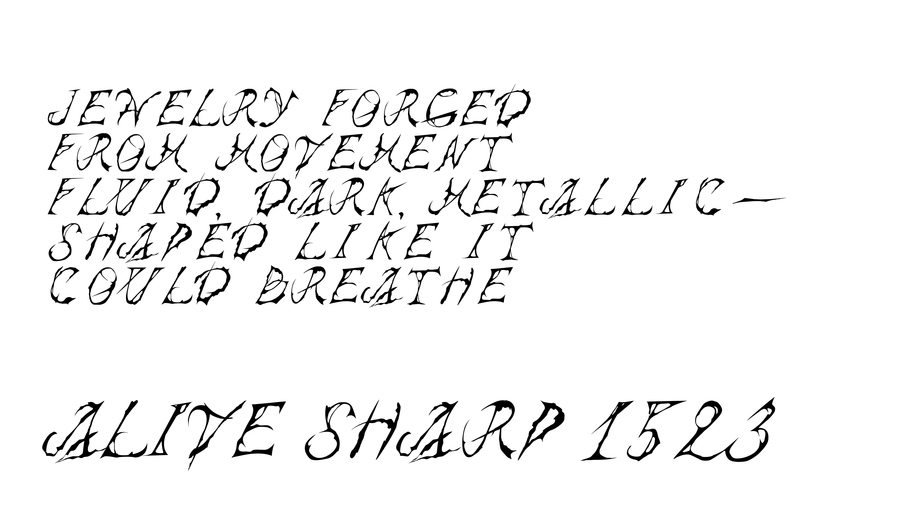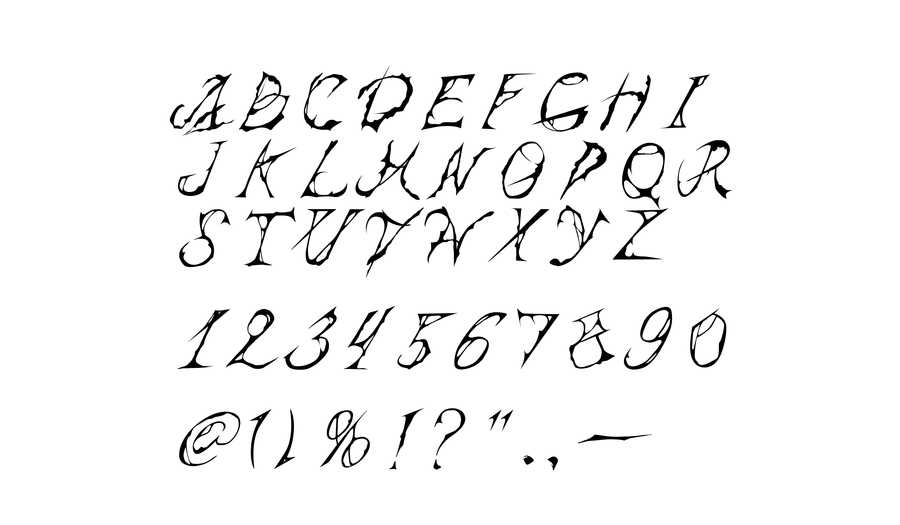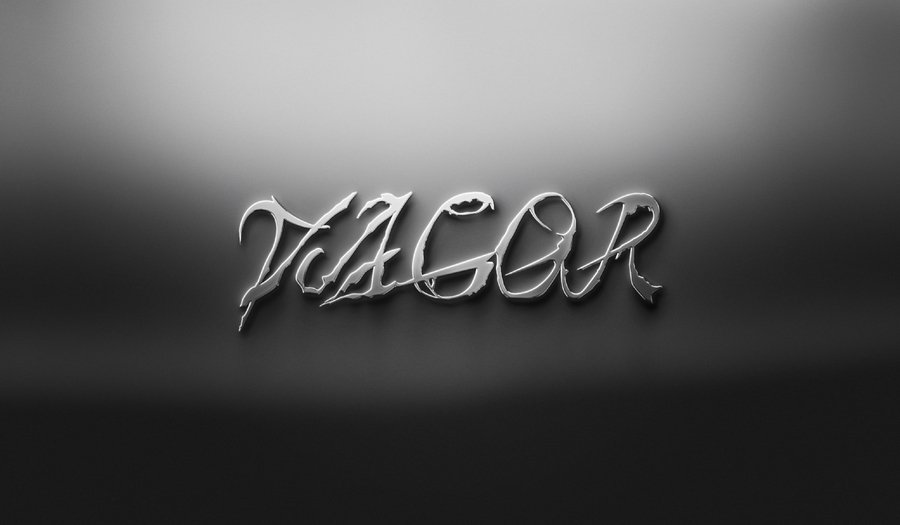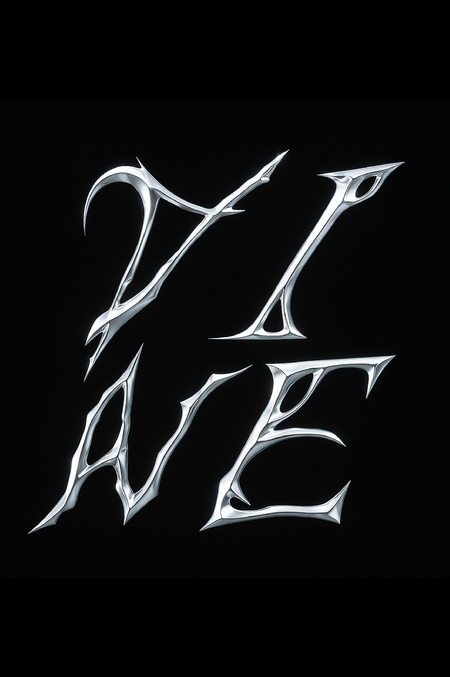
vine — акцидентный шрифт
Vine — это живой, динамичный шрифт, созданный для проектов, в которых важны индивидуальность и выразительность
Его характер строится на контрасте острых и мягких линий, на сочетании спонтанности и внутреннего ритма